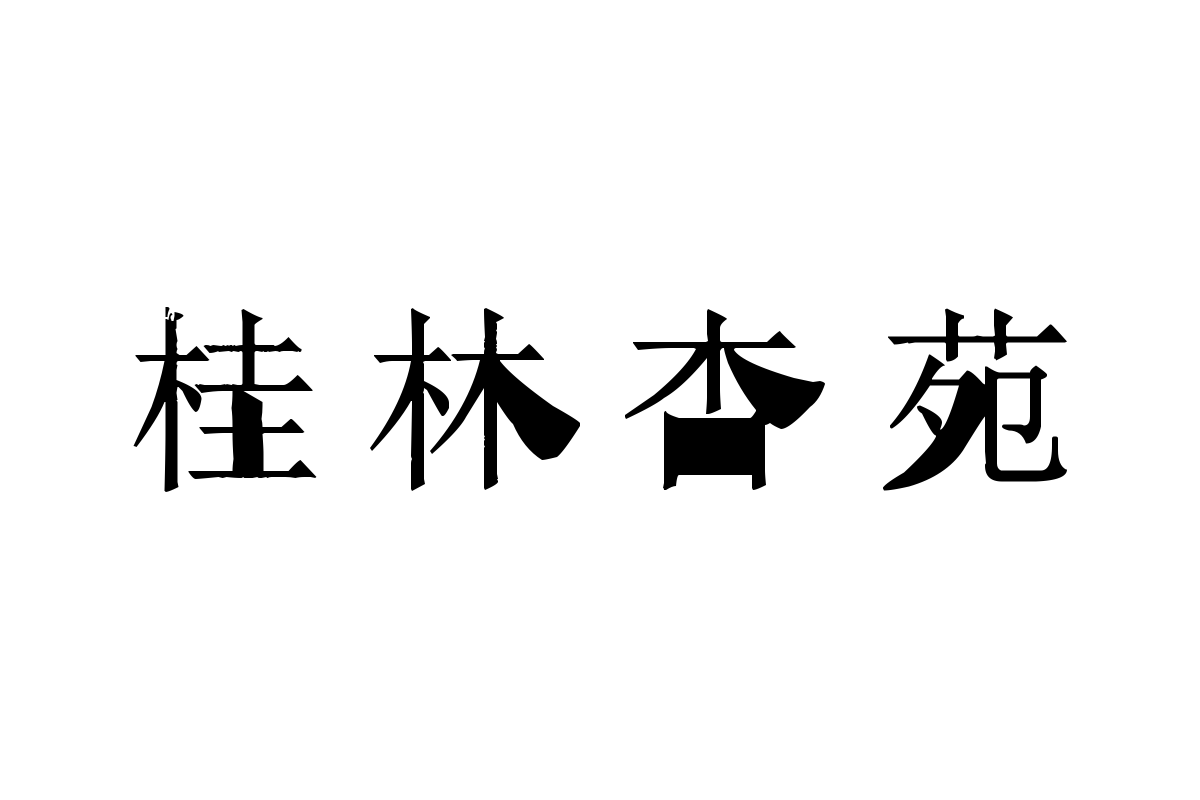
汉呈王天喜宋变字体是一款具有独特风格和特色的中文字体。这款字体的设计灵感来源于中国的传统书法艺术,将汉字的笔画、结构和形态进行了巧妙的融合和创新。其特点是字形圆润饱满,线条流畅自然,给人一种优雅、庄重的感觉。同时,字体中的笔画粗细变化丰富,既有粗犷豪放的气势,又有细腻精致的韵味,非常适合用于需要强调文字个性和艺术感的场合。